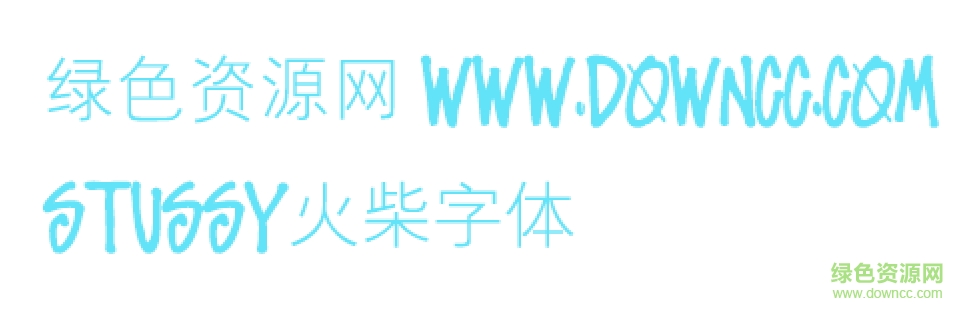
stussy字体即Stussy Script火柴字体。这款字体非常有特色,适用于设计海报,广告制作等方面。欢迎感兴趣的用户来绿色资源网下载使用。
stussy字体是一款非常实用的中文字体,该字体线条粗细适中,中文字体端正大方,英文字形飘逸大方,整体风格非常的出色,并且字库完整,可用于艺术设计、包装印刷、签名设计、图形设计等领域